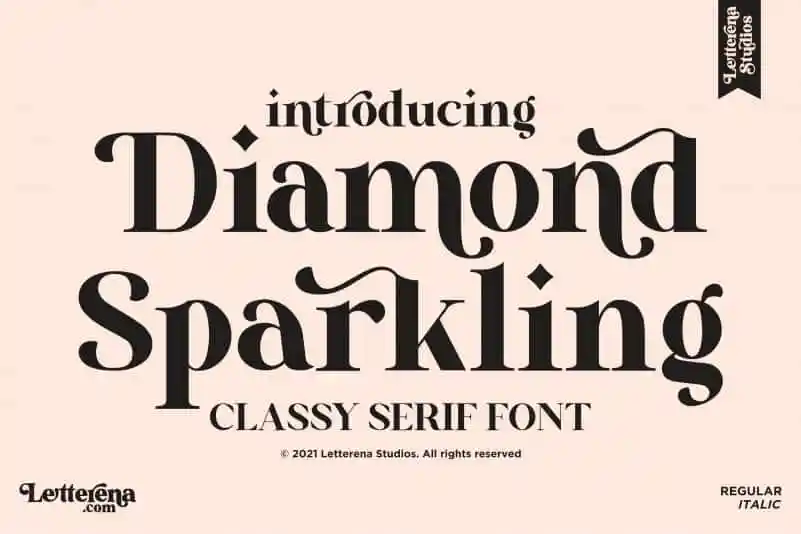
Diamond Sparkling Serif Font – Download Grátis
A Diamond Sparkling Serif Font é uma elegante escolha para projetos que exigem sofisticação e luxo. Desenvolvida pela Letterena Studios, esta serif font foi criada para atender às necessidades de diversos tipos de trabalho, desde a criação de logotipos até o design de etiquetas, passando por materiais como capas de livro, convites e cartões de visita. Suave mas poderosa, ela se destaca em designs variados que exigem uma aparição sofisticada e luxuosa. Seja para um novo produto ou embalagem personalizada, para roupas customizadas ou até mesmo para criações gráficas destinadas a eventos especiais, esta font traz estilo único à qualquer projeto. Com Diamond Sparkling Serif Font, você pode adicionar o toque final de luxo e elegância aos seus trabalhos mais expositivos. A combinação perfeita entre aparência e funcionalidade, essa serif permite que qualquer designer gráfico transforme suas ideias em arte vibrante, criando um impacto visual que destaca seu trabalho e eleva-o ao nível dos mais sofisticados projetos. Com Diamond Sparkling Serif Font, você consegue alcançar uma qualidade superior, sempre mantendo-se fiel à sua identidade pessoal e ao estilo único de seus trabalhos.